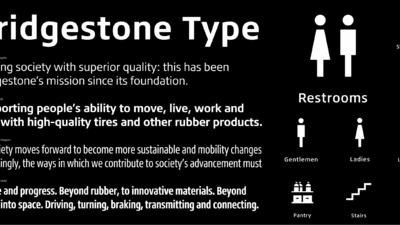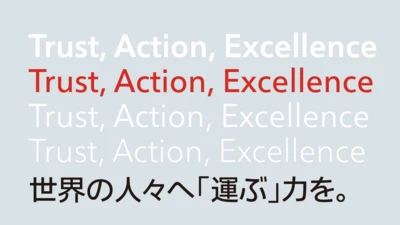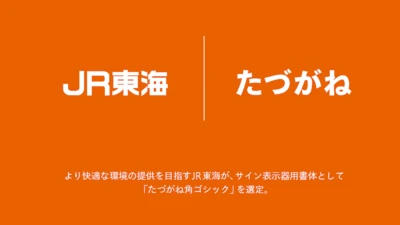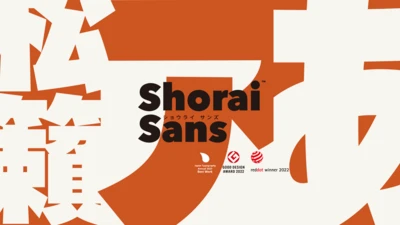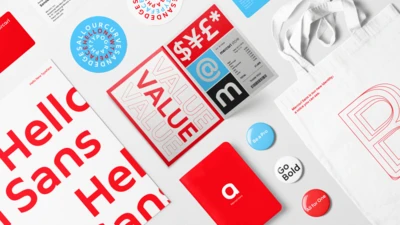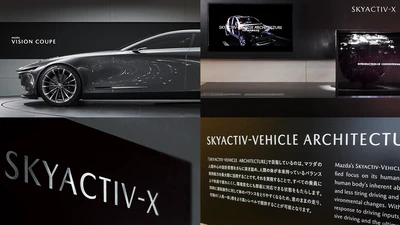
AQUOS 最新シリーズのシステムフォントにたづがね角ゴシックInfo を搭載
AQUOS最新シリーズのシステムフォントにたづがね角ゴシック Infoを搭載
LINEヤフー株式会社のコーポレートフォント「LINE Seed JP」。その制作背景と、導入後の多彩な活用事例をご紹介します。
LINEヤフー「LINE Seed JP」 コーポレートフォント開発
1575 年から続く香の名跡「香十」を受け継ぎ、お線香やお香、そしてフレグランスブランドを、国内のみならず世界へと展開している日本香堂グループ。2025 年には450 年の節目を迎えるにあたり、「450プロジェクト “聞く~awake your spirit~”」として、新事業や新製品を含む多彩な取り組みを発表しました。
その嚆矢となったのが、新たに定められたグループアイデンティティです。グループおよびコーポレートのロゴタイプは、サン・アドのアートディレクター葛西薫氏と、Monotype® のクリエイティブ・タイプディレクター 小林章の協働によって制作されました。
日本香堂グループ ロゴマーク制作
「Wesmo!(ウェスモ)」はJR西日本(西日本旅客鉄道)が提供する決済サービス。地域や価値観の隔たりをなくし、人、まち、社会がつながる理想を思い描いて、動くことを価値にする─「Moving is Value.」をブランドコンセプトとして生まれました。そのリリースに合わせて取り組んだのが、オリジナルフォントWESTERX Sansの開発です。
クライアントであるJR西日本 WESTER-X事業部、Wesmo!のサービスブランディングを手がけるセイタロウデザインの山崎晴太郎氏と共に、ブランドの声となるフォントをMonotypeで制作しました。
ブランドのパーソナリティーを体現する JR西日本のオリジナルフォント「WESTERX Sans」開発
Monotype は、 世界的に愛される自動車メーカーの一つであるマツダ株式会社のクルマのオーナメントに使用する英数字フォントを制作しました。
Mazda Type
Bridgestone Type
Monotypeは、タイヤ・ゴム業界におけるグローバルリーディングカンパニー、株式会社ブリヂストンの欧文コーポレートフォントを制作しました。完成したオリジナルの欧文コーポレートフォント Bridgestone Typeのファミリーは、Regular、Medium、Boldとそれぞれのイタリック体、コンデンス体を合わせた計12ウェイト。高い可読性、視覚的な安定感、多様なメディアでの明瞭性、コンパクトな字幅によるスペースの節約、シンプルなエレメントによる機能美を備えており、ブリヂストンらしいブランド表現の核として様々なグラフィックデザイン、ロゴや対外発表などあらゆるタッチポイントで積極的に活用されています。
Isuzu AN
Monotypeは、世界トップクラスの商用車メーカー、いすゞ自動車株式会社の専用書体を制作しました。欧文書体については、社内で使用していたAvenir Nextの硬質な印象を残しながら、画面上での可読性や実用性を考慮して調整。8ウェイトの専用書体Isuzu ANを制作しました。Avenir Next の多言語ファミリーを使用したよりグローバルな展開も可能です。また和文書体には、Avenir NextにあわせてMonotypeが開発したShorai Sansを採用し、Isuzu ANと組み合わせて使える4ウェイトが指定されました。
いすゞ自動車の専用書体は、機能性とブランドを兼ね備えた書体として、同社の製品やメッセージに幅広く使われる予定です。